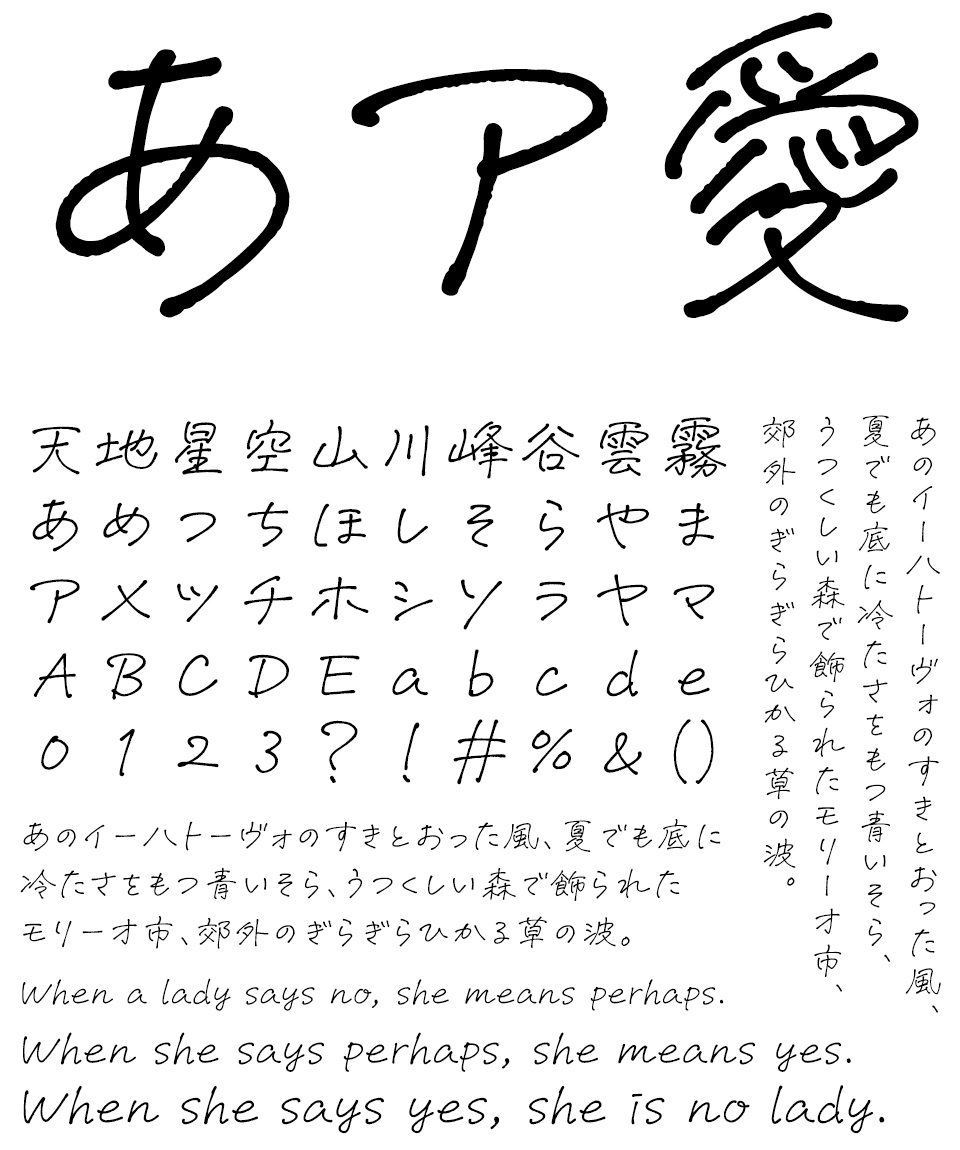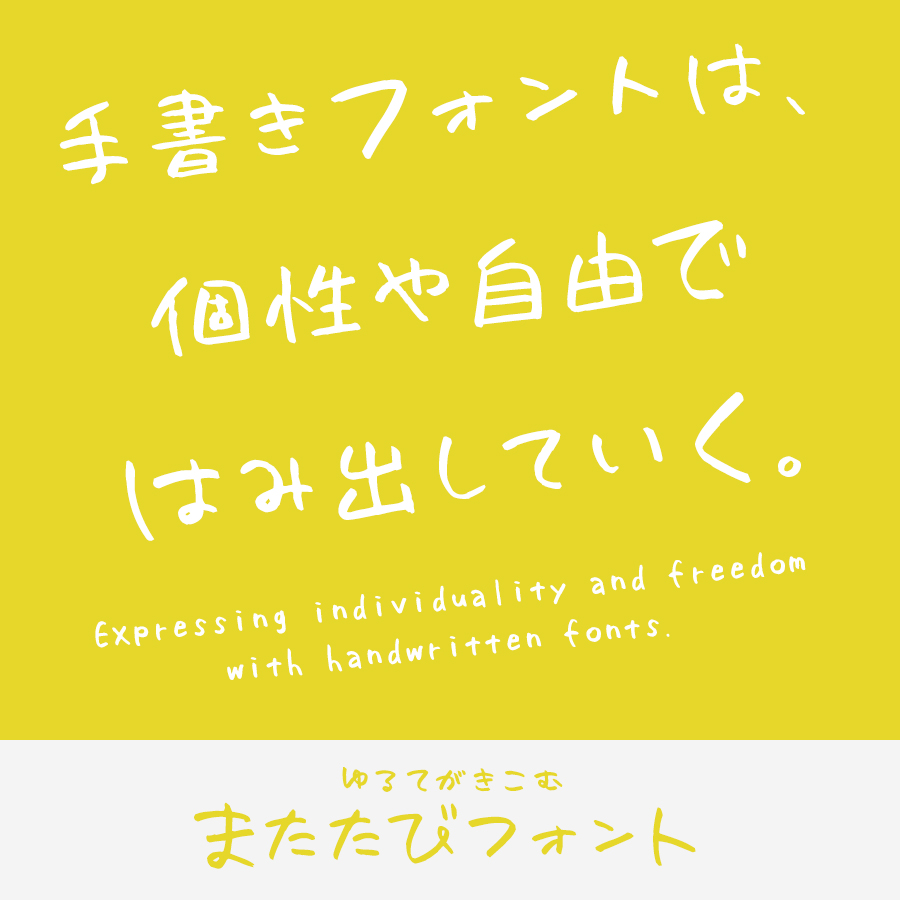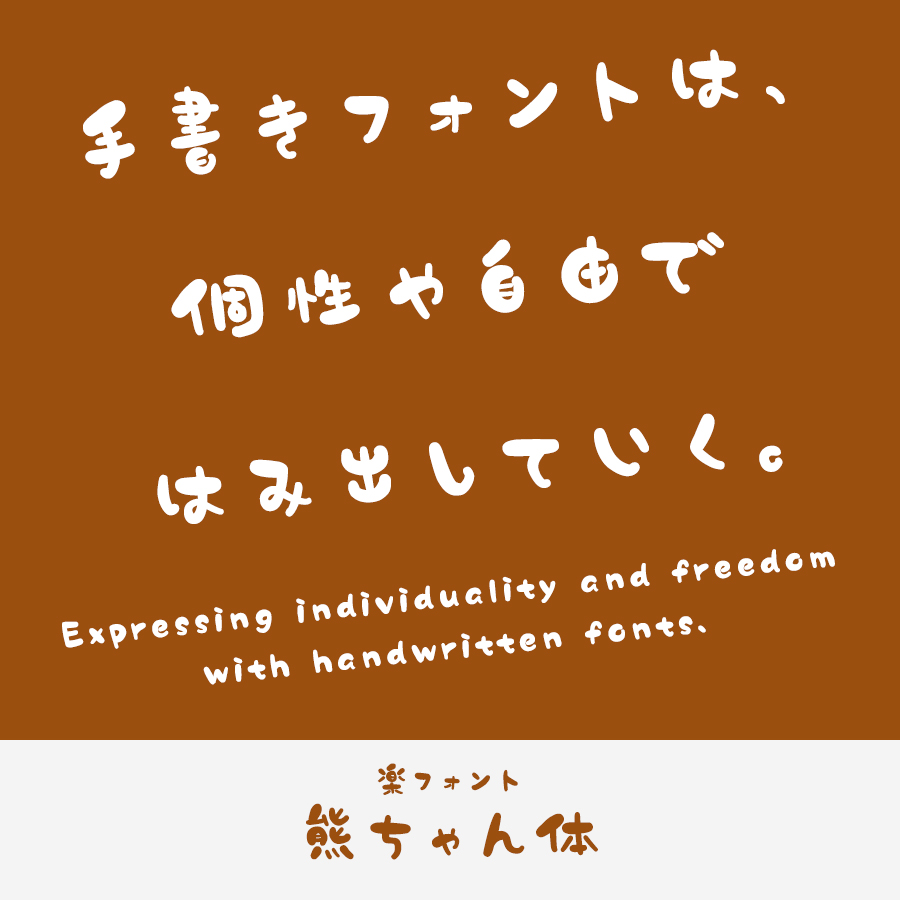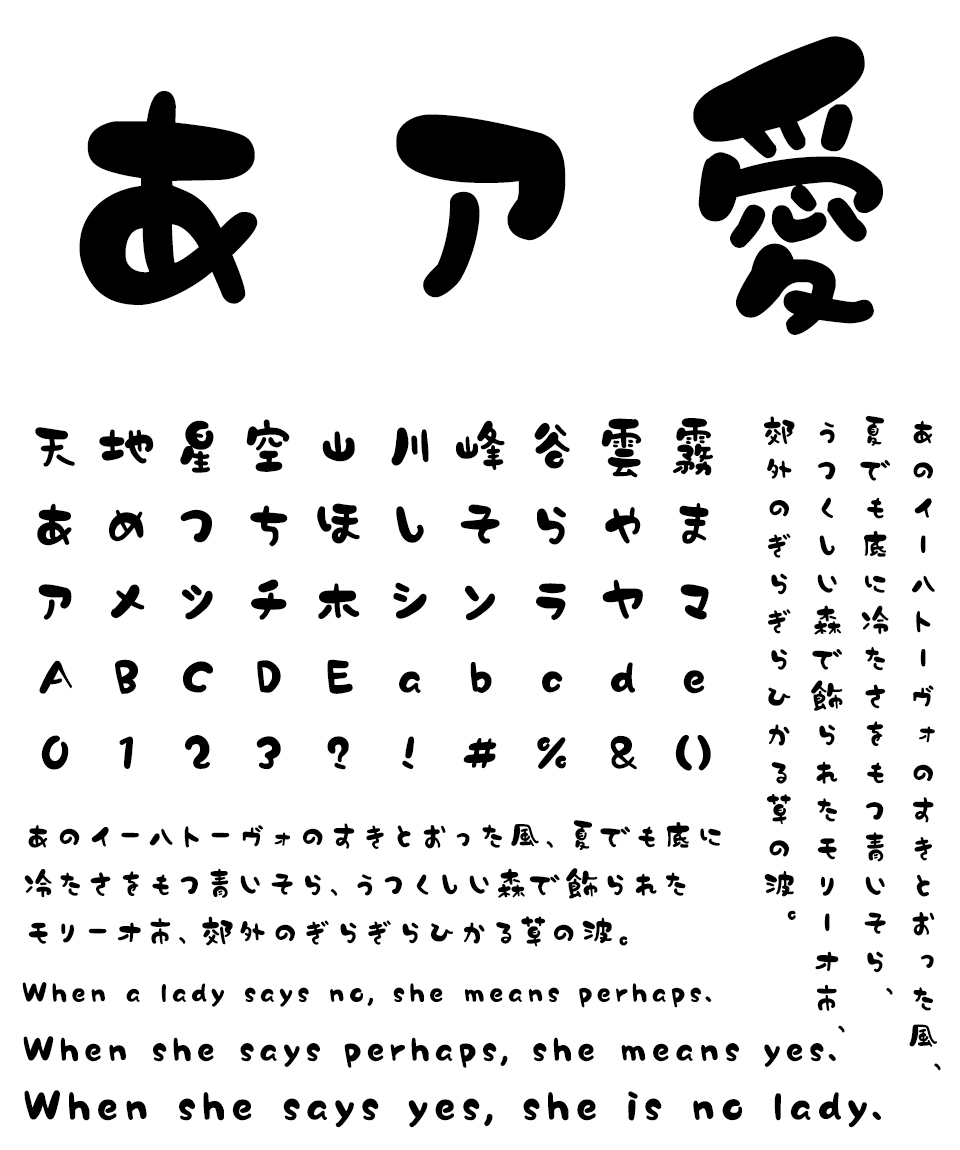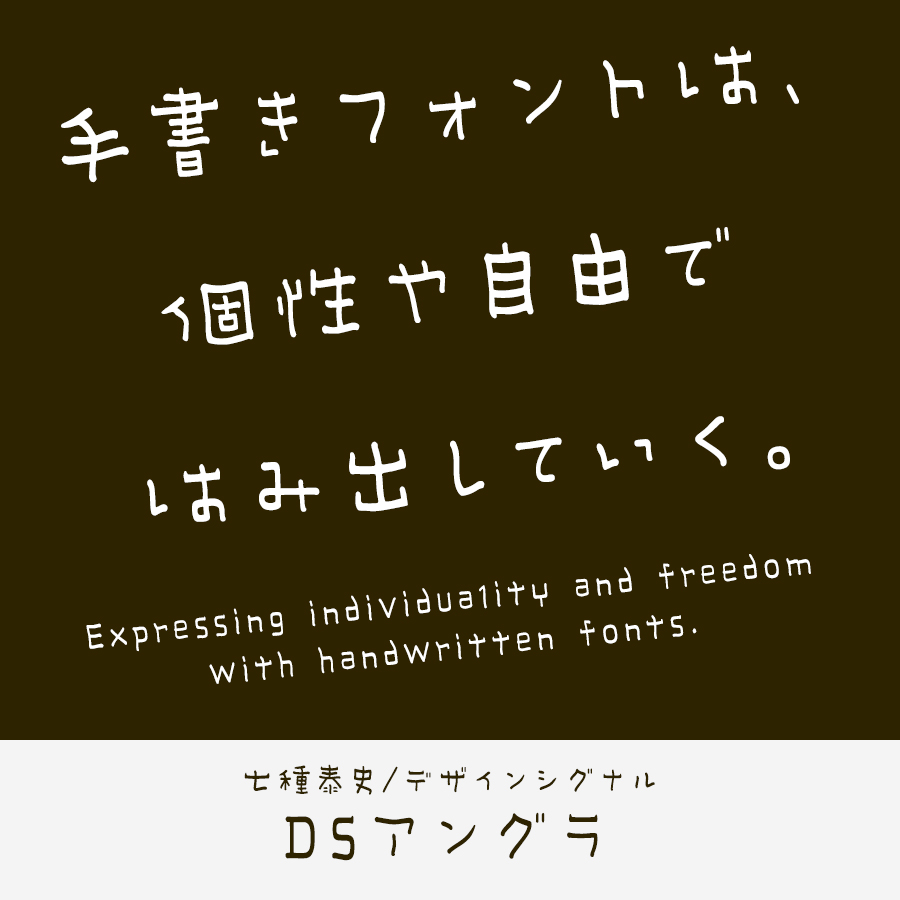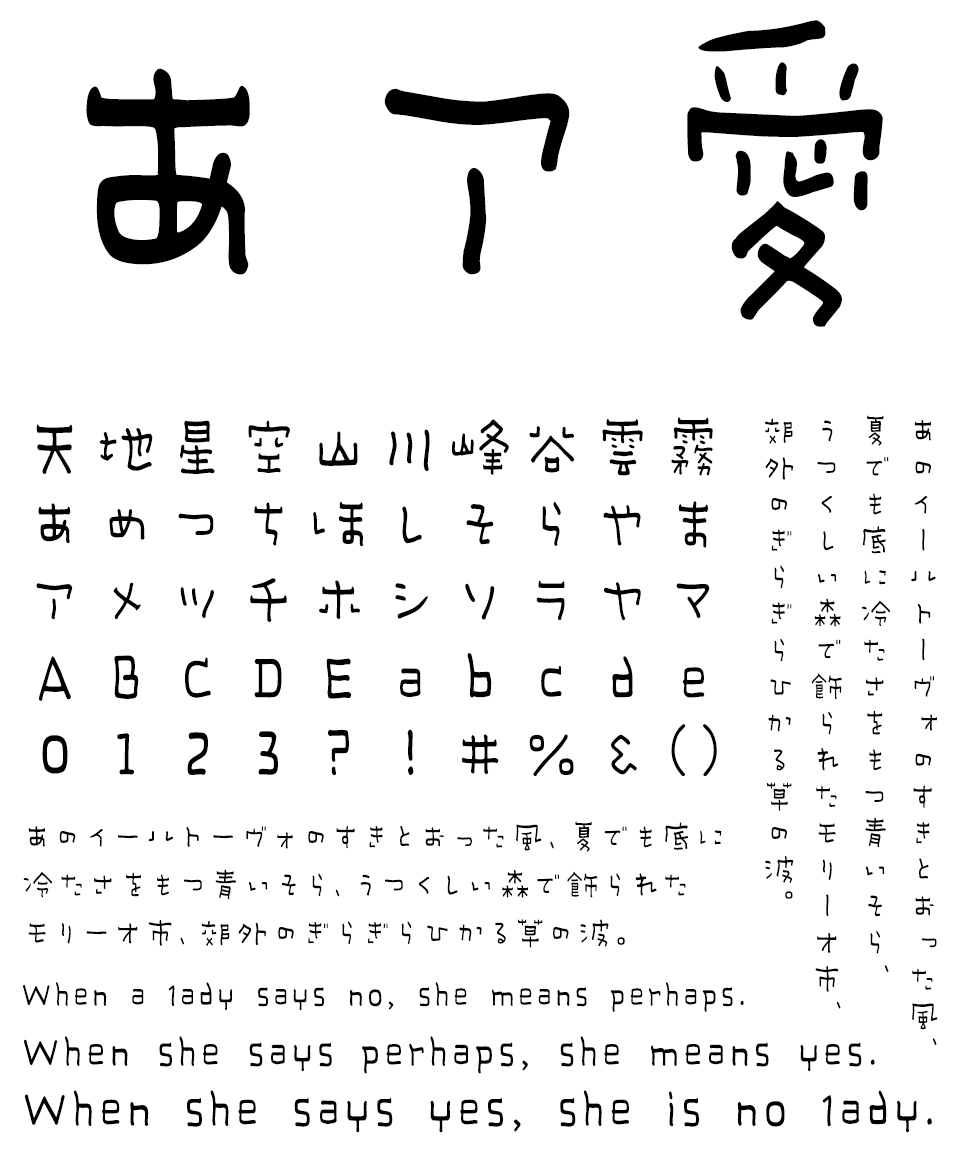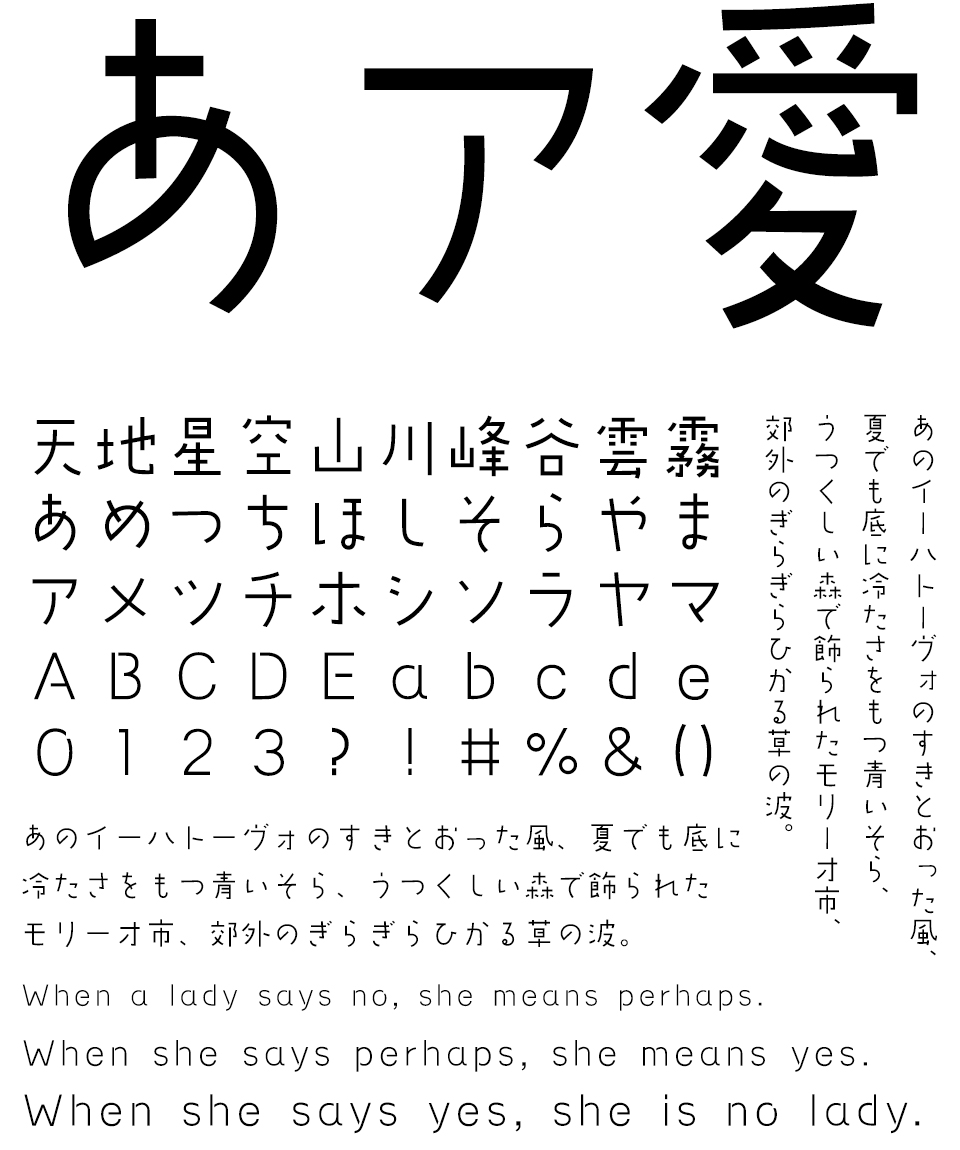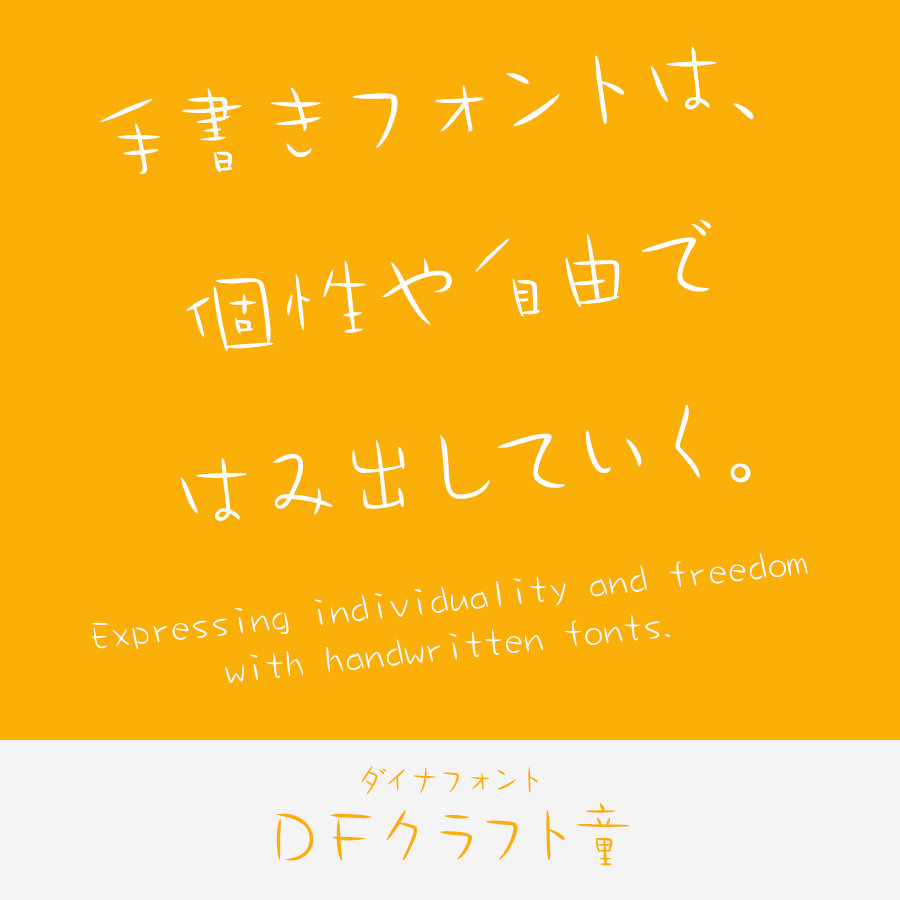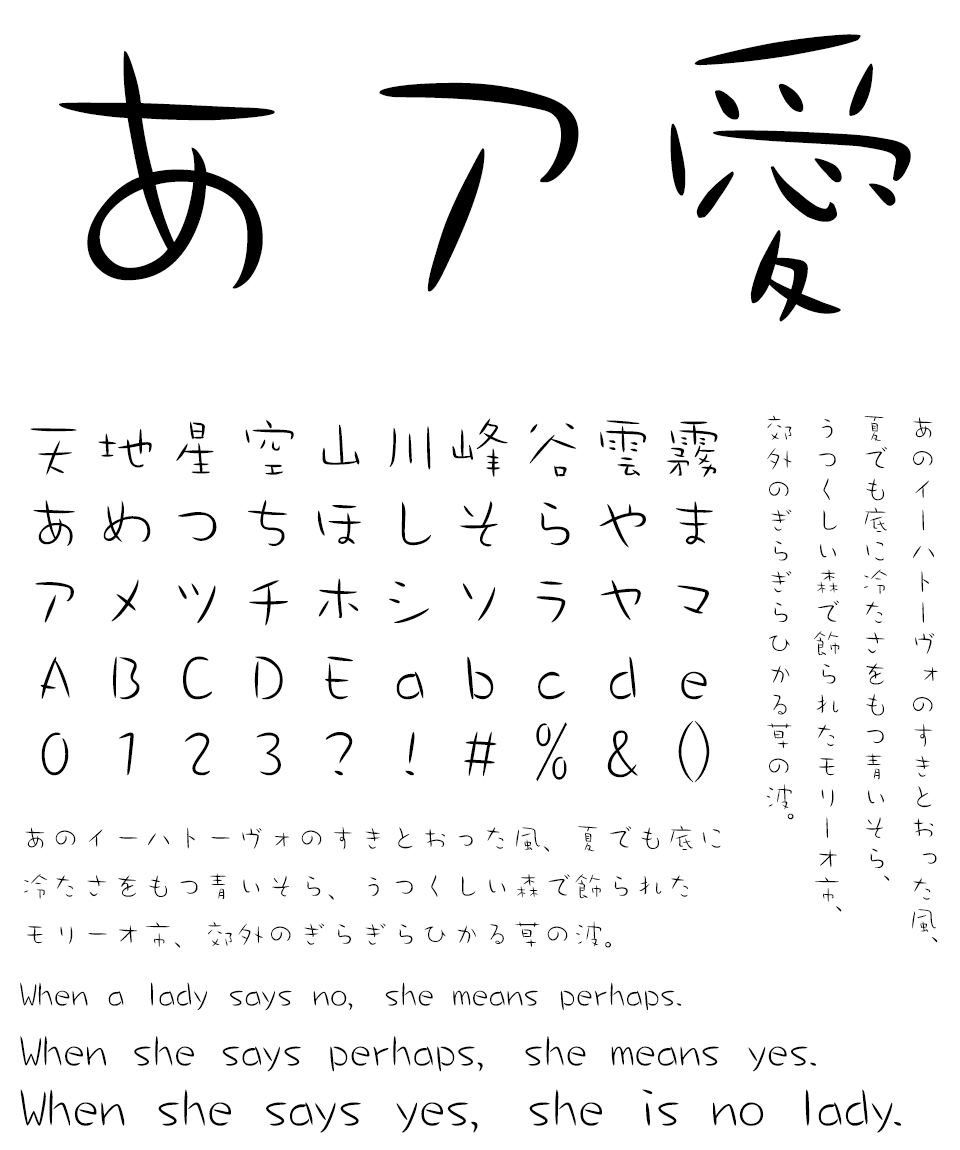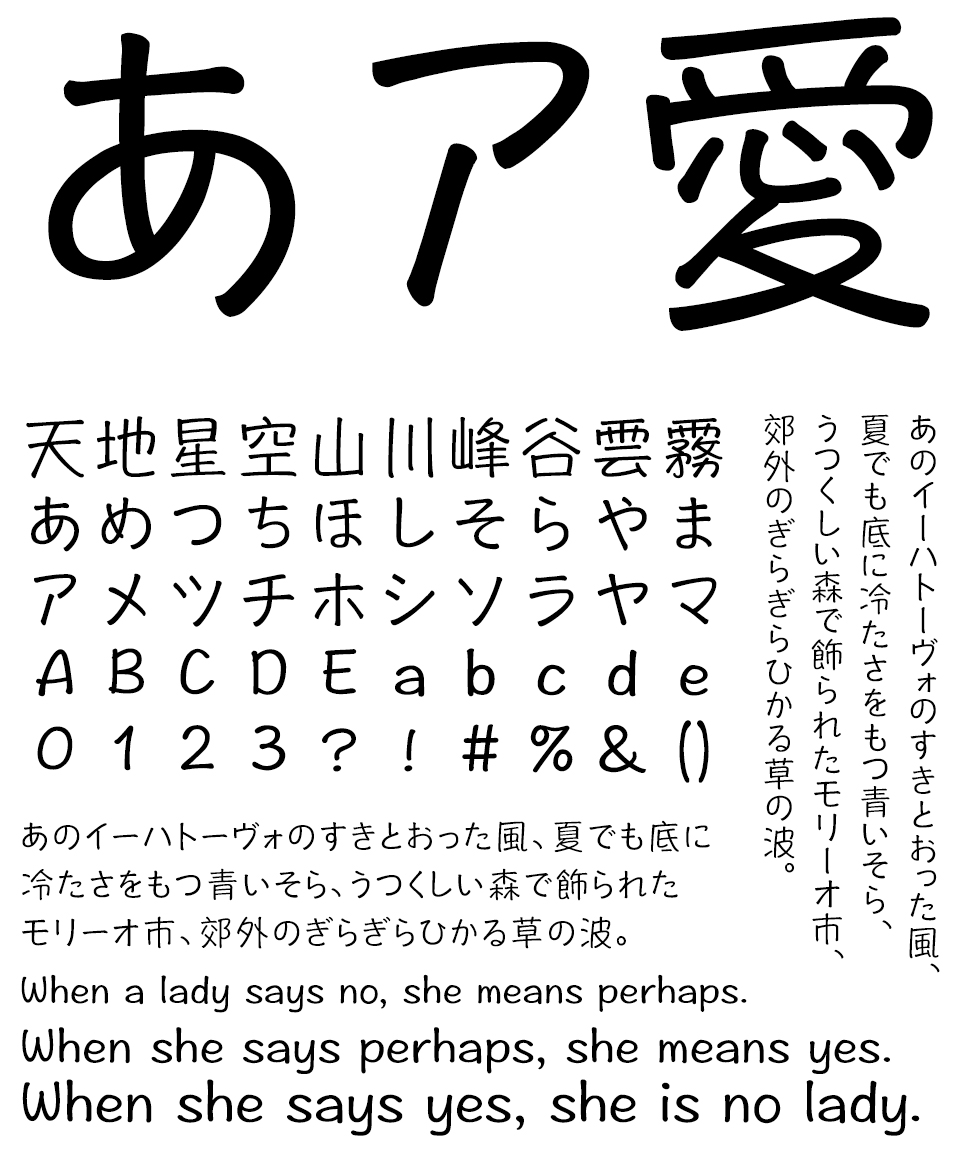
リアル手書き、手書き風の日本語フォントを厳選
使用フォント:空とひこうき / 花とちょうちょ
アナログ風・手書き風のクリエイティブデザインには、《親しみのある雰囲気を演出できる》《デジタルが主流の中で目立ちやすい》など、消費者に響きやすいメリットがあります。そのためBtoCの企業を中心によく見られるようになりました。
そんなアナログ風・手書き風のデザインに欠かせないのが、手作り感と温もりが伝わる手書きフォント。商品の特徴を説明するキャプションで使用するのにも適しますし、感情が伝わりやすい見た目の利点を活かし、お客様やスタッフからのコメントに使用するのも効果的です。
手書きフォントの種類
デザインポケットでは、手書き系のフォントを「リアル手書き」「手書き風」の2種類に分類してご案内しています。
リアル手書きフォント
実際に紙に書いた文字をスキャンするなど、手書き文字そのものの再現を重視した制作過程により、本当の手書き文字のような見た目と使い勝手が得られる書体です。
いわゆる「きれいめ」の書体を選べば、商品説明・スタッフコメントなどの長文でも可読性を損なわず、丁寧さや信頼感の溢れる使い方に。一方で、「へたうま」といわれるような個性的な書体であれば、見出しなどのポイントに利用することでインパクトが生まれ、例えば飲食店のメニューなどに重宝します。
手書き風フォント
手書きの味わいや柔らかさを残しながらも、より滑らかに整頓された輪郭や骨格も併せ持った書体です。例えば、手書きのロゴや手書き文字を、丁寧にレタリング加工し直したようなものがあります。
リアル手書きの書体に比べると全般にエレメントが丁寧に整っており、しっかりとした太さのある書体も数多く揃っています。そのため、どちらかといえば短めの文字列を強く印象づけたい用途に適し、商品ロゴや書籍の表題、映像作品のタイトルなどによく利用されます。
特徴とメリット
「リアル手書きフォント」「手書き風フォント」どちらも、「温かみ」や「優しさ」が最大の特徴。角ゴシック体や明朝体にはない「やわらかな印象」を与えてくれます。
アナログ感を演出し、見た人の興味を引くことができるという特性を活かし、タイトルやアクセントとしてポイントで配置したり、「個性」や「人間味」「信頼性」を伝えるためのメッセージなどに用いると効果的です。
収録文字数1万5000〜2万超 Pro以上のフォント
そして、よりマイナーな異体字や、ほぼ学術分野でしか使わない漢字など、さらに使用頻度が低い文字までを含むのがAdobe-Japan1-4以上の文字セットです。
メーカーによって若干の違いがありますが、例えばAdobe-Japan1-4準拠ならば「Pro」、Adobe-Japan1-5準拠ならば「Pr5」といった記号をフォント名に冠するのが一般的です。
一方で、これらPro以上のフォントの大半は、明朝体と角ゴシック体に集中しています。
手書きや毛筆、デザイン系のフォントの場合、滅多に使わないような文字に対するニーズは少なく、文字セットはJIS第2水準あるいはAdobe-Japan1-3までがほとんど。Adobe-Japan1-4以上に対応した製品はほんの少ししかありません。
図解フォント JIS規格・Adobe規格 各規格に含まれる漢字に注目した関係図
Adobe-Japan1-7が最新
最近になってAdobe-Japan1-7という規格も登場しています。これは、Adobe-Japan1-6に「㋿」(令和の合字) 1文字を加えただけの文字セットです。
メーカーによっては、既存製品 (たとえばAdobe-Japan1-3対応のStdフォント) にこの1文字を追加したことを「Adobe-Japan1-7対応」と表現することもありますのでご注意ください。
JIS90字形とJIS2004字形 (Nなし・Nあり)
2004年、漢字のうち168文字の「お手本」が改められた
長く日本語フォントの拠り所とされて来たJIS規格に、2004年、ちょっと大きな変更が加わりました。何千とある漢字のうち168文字について、文字のお手本ともいえる「例示字形」に変更が加えられたのです。
それぞれの規格の正式名称をぎゅっと縮め、変更が加わる前の文字セットを「JIS90」、変更後の文字セットを「JIS2004」と呼んでいます。
何がどう変わった?
この「お手本変更」でよく挙げられる好例が「辻」。従来は一点しんにょうが標準とされたこの字、JIS2004では二点しんにょうに変更されました。その他、気づきやすい字形変更の例としては葛飾区の「葛」、祇園の「祇」、見た目の印象が大きく変わる「溢」などが挙げられます。
全体を眺めると、略字風を標準としてきたJIS90に対し、JIS2004ではより古典的な「正字」を標準とするように改められています。なお、168の変更の中には、たとえば筆文字で書けば全く差がないような、ごく僅かな違いしかないものもあります。
Design筆文字Font
デコフォントマリーTWINS
遠山銀波が描いたユルい書体。マリーWH(白)・マリーBK(黒)の2書体を収録。WHをベースとした文中に所々BKを入れてみても面白い手書きフォントです。